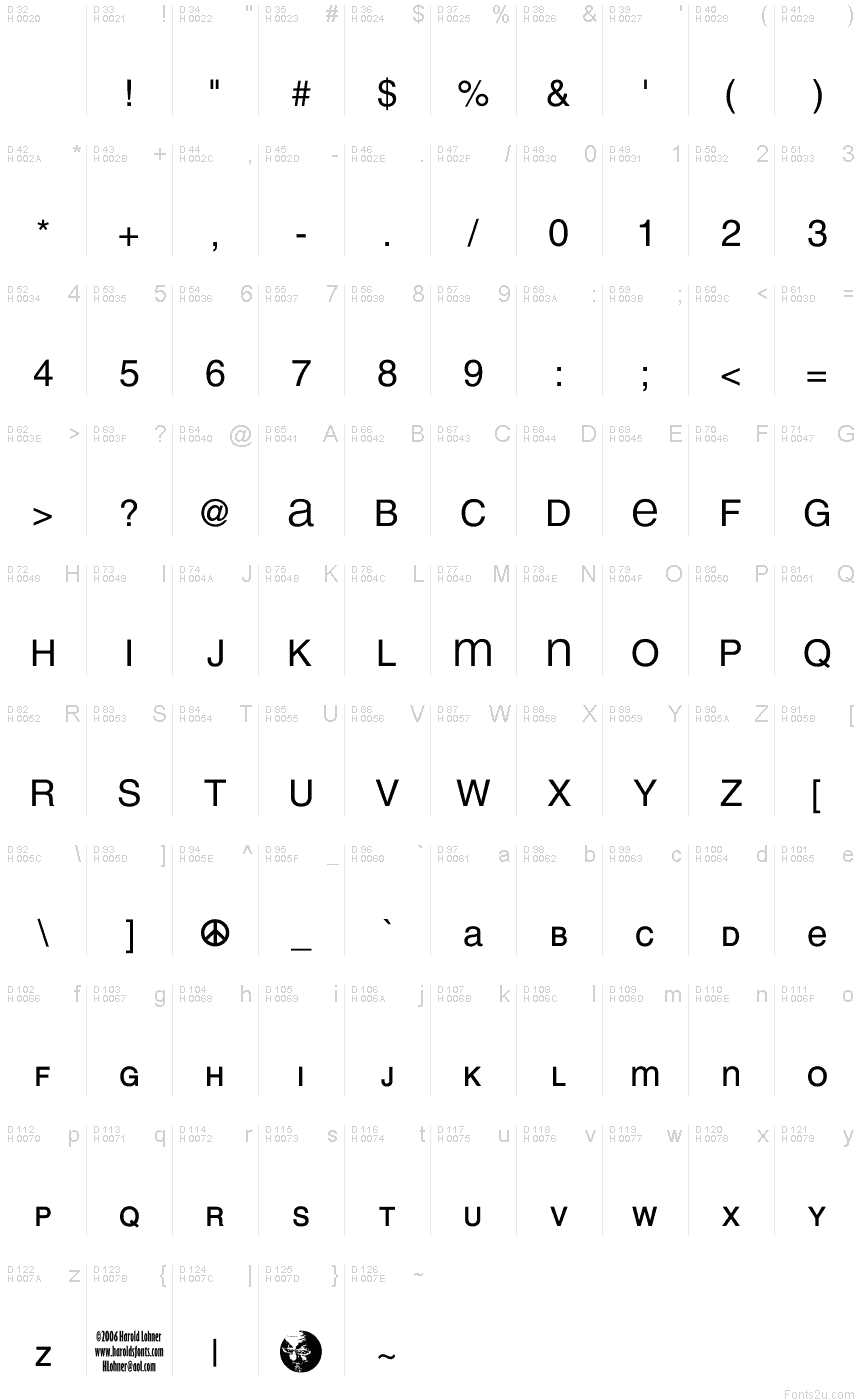
MEAN 26 Sans
Mean 26 Sans autorstwa Harolda Lohnera to darmowy krój bezszeryfowy oparty na koncepcji Alphabet 26 Bradbury’ego Thompsona. Litery zostały tu zredukowane do gładkich, elementarnych kształtów o niemal diagramowym spokoju. Szerokie, obłe brzuszki i proste linie pionowe tworzą równy rytm, który sprawia wrażenie celowo uproszczonego, a nie tylko neutralnego.
To naturalny wybór do grafik edukacyjnych, opisów muzealnych, minimalistycznych plakatów, szkiców logo i opakowań, które potrzebują oszczędnego wyrazu typograficznego. Dzięki temu, że formy wyglądają na destylowane, a nie ozdobne, MEAN 26 Sans świetnie sprawdzi się w krótkich nagłówkach i oznaczeniach, przy których zwykły krój bezszeryfowy wydałby się zbyt pospolity.